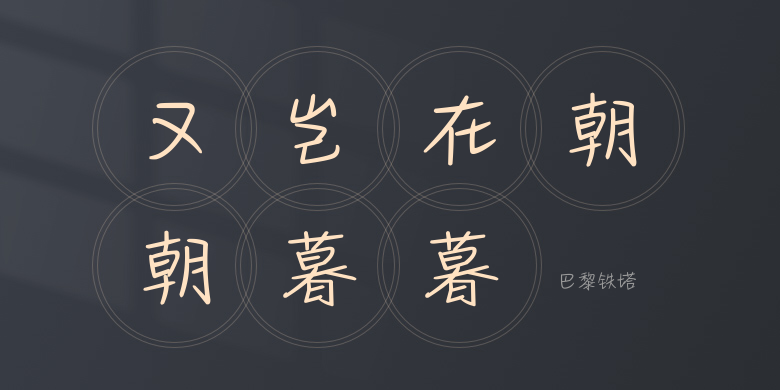
巴黎铁塔
巴黎铁塔,这款字体结构工整、笔画清晰,兼顾美观与易读性,适用于标题、正文、海报、包装、LOGO 等多种场景。字形优雅稳定,风格百搭耐看,适配日常排版与创意设计,让文字呈现更舒适、更具质感。巴黎铁塔一笔一画,皆是细节,以均衡的比例、流畅的线条打造舒适视觉体验,字形端正大气,风格简约现代。无论是商业设计、品牌宣传还是日常排版,都能轻松驾驭,让文字更有格调与力量。巴黎铁塔字体下载。